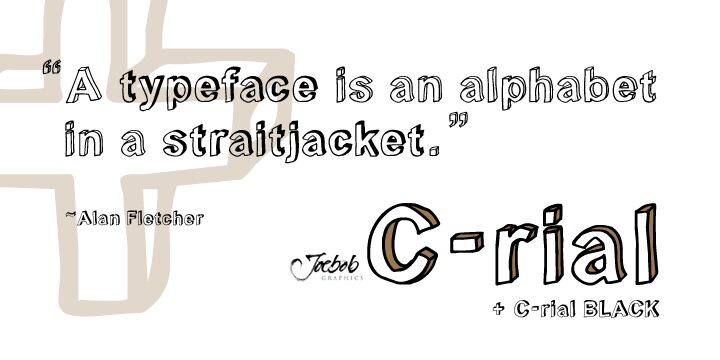
C-rial od J O E B O B graphics to darmowy font typu display 3D z otwartym obrysem i ostro przesuniętymi krawędziami, które nadają każdemu znakowi charakter przypominający złożone znaki przestrzenne. Nieregularne kontury łagodzą geometrię, tworząc swobodne, ręcznie rysowane podejście do trójwymiarowego liternictwa.
Kątowa głębia tworzy efekt wycinanki, świetny w tytułach na plakatach i grafikach muzycznych, a luźne obrysy dodają nieformalnego pazura ulotkom i młodzieżowym projektom. Wykorzystaj ten darmowy font w projektach naklejek czy zabawnych opakowań, wszędzie tam, gdzie liternictwo ma współgrać z ilustracją i oddawać tę samą szkicową, konstrukcyjną energię.